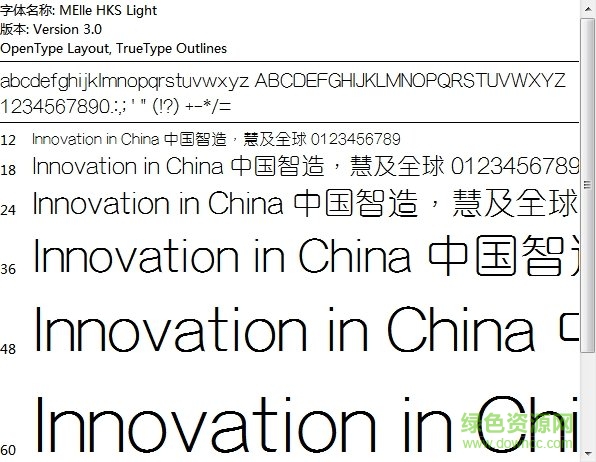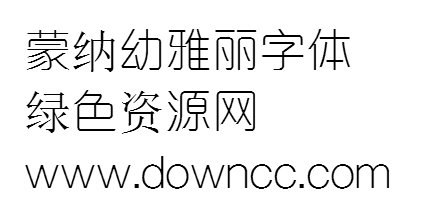
蒙納幼雅麗體
簡幼雅麗是蒙納字體雅麗體系列的纖細(xì)版,字跡十分娟秀清爽,造型大方斷針,有著綿延清麗的外觀結(jié)構(gòu),如果你喜歡,可以來綠色資源網(wǎng)試試哦!
蒙納幼雅麗體簡字體說明
蒙納簡幼雅麗字體
蒙納幼雅麗體是蒙納雅麗系列的light版,其他包括蒙納簡雅麗體、蒙納簡粗雅麗字體等,風(fēng)格上比較接近,但筆畫深淺上各有特色。可以使用在藝術(shù)設(shè)計、平面設(shè)計、廣告設(shè)計、包裝設(shè)計等場合。